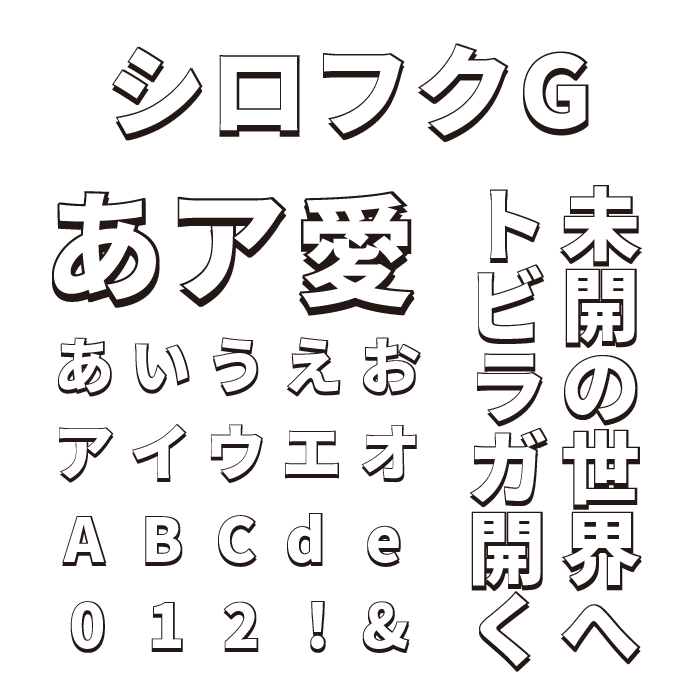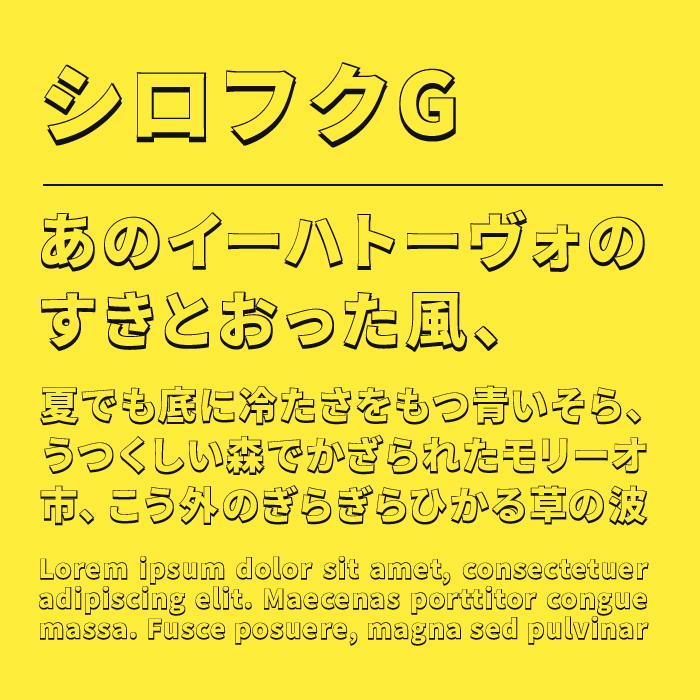
シロフクGフォントは、袋文字になった文字に影がついたようなユニークなゴシック体です。
立体感のあるレイヤー効果が施されており、見た目にインパクトがありますが、整った骨格のおかげで読みやすさも損なわれていません。遊び心がありつつも、しっかりと安定感を持つバランスが魅力なフォントです。
特に背景色とのコントラストを活かしたデザインで映えるフォントで、少し情報を目立たせたい時にぴったりなデザインです。楽しくて親しみやすい印象を与えたい時に重宝するフォントです。
フォントの文字見本
収録文字は、漢字・ひらがな・カタカナ・アルファベット・数字・記号が収録。